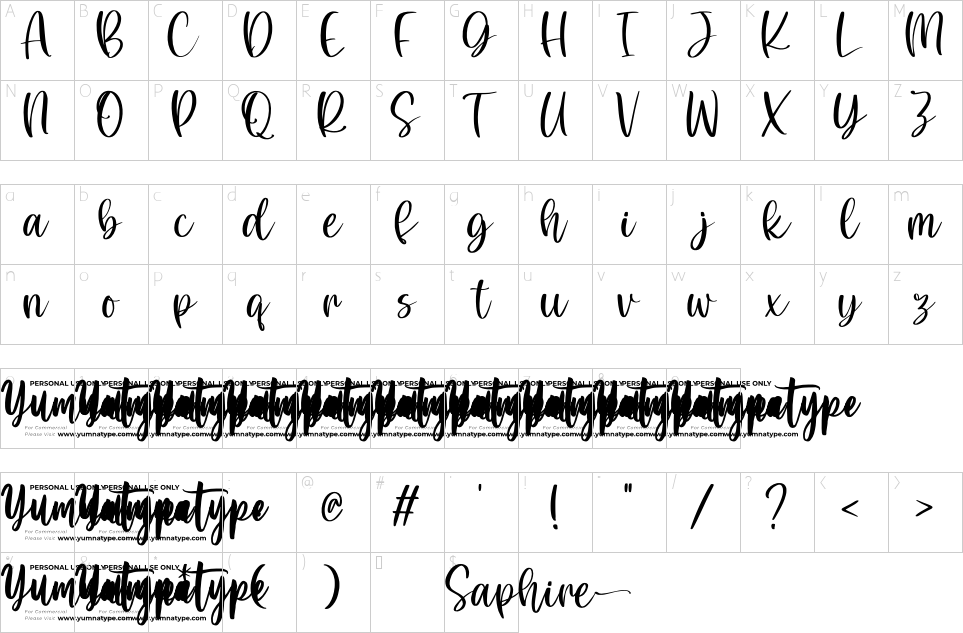
Saphire Font – Download Grátis
Descubra a beleza da Saphire Font para seu próximo projeto gráfico. Desenhada pela Yumna Type, esta elegante fonte está disponível tanto no Windows quanto no Mac e já foi baixada 3,805 vezes por designers atentos ao detalhe. Seu design minimalista e sofisticado é perfeito para criar um texto visual atraente sem comprometer o estilo único de sua marca. Experimente agora e transforme suas ideias em arte com esta fonte de alta qualidade e facilidade de uso.